[Tải miễn phí] 10 Font chữ độc,đẹp, lạ cho "dân đồ họa"
Dưới đây, chúng tôi sẽ giới thiệu cho các bạn 10 font chữ đỉnh cao nhất và chất lượng nhất cho thiết kế, hãy tải miễn phí font chữ cho design dưới đây, để tạo nên những tác phẩm kinh điển của bạn.
Các bộ sưu tập mới của các phông chữ miễn phí tốt nhất cho các nhà thiết kế. Font thương mại sử dụng phải có chất lượng cao nhất có sẵn để tải về miễn phí cho bạn. Những phông chữ này có thể sử dụng làm tiêu đề , thẻ kinh doanh, thiết kế tờ rơi…. Hãy khám phá những pont chữ mới cùng chúng tôi nhé.
1. Font Slot
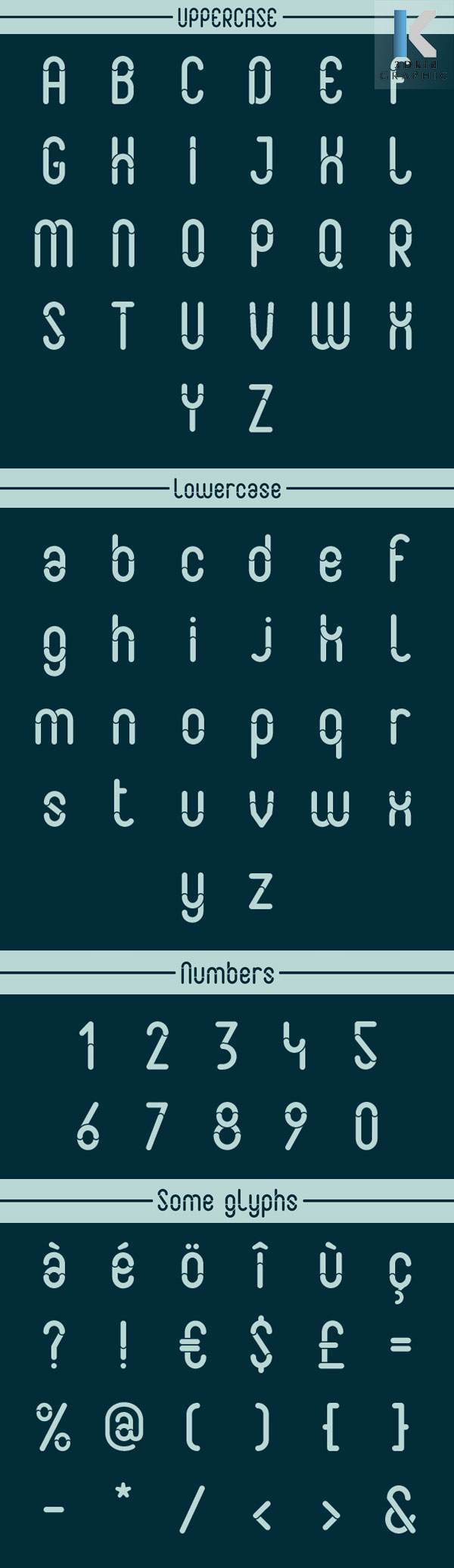
2. Font Kagome
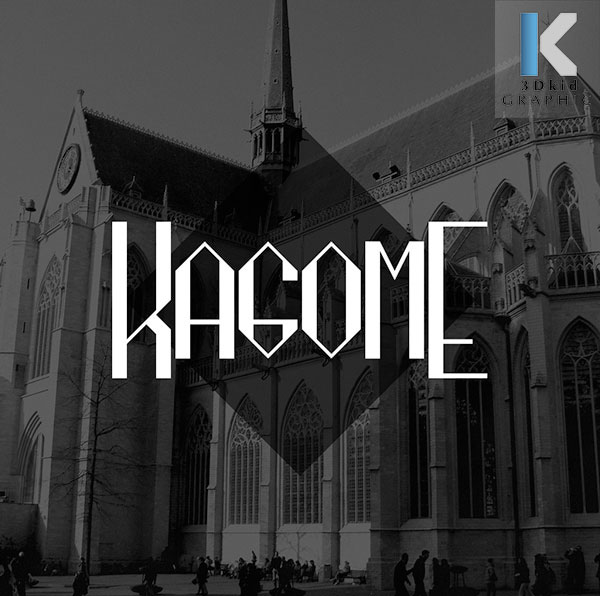
3. Font Daggerspuare
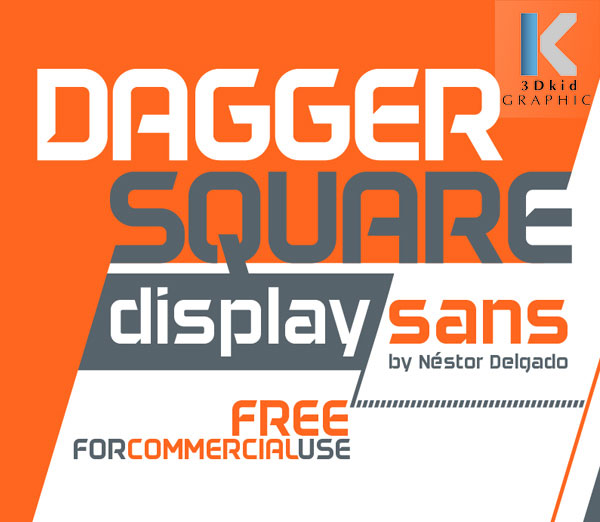
4. Font Monthoers
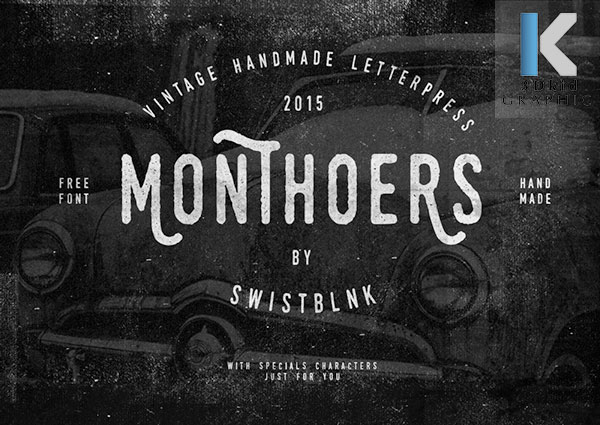
5. Font Nordic
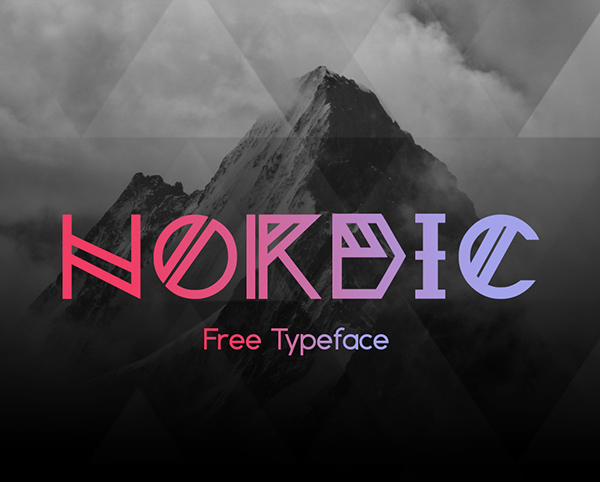
6. Font Moon
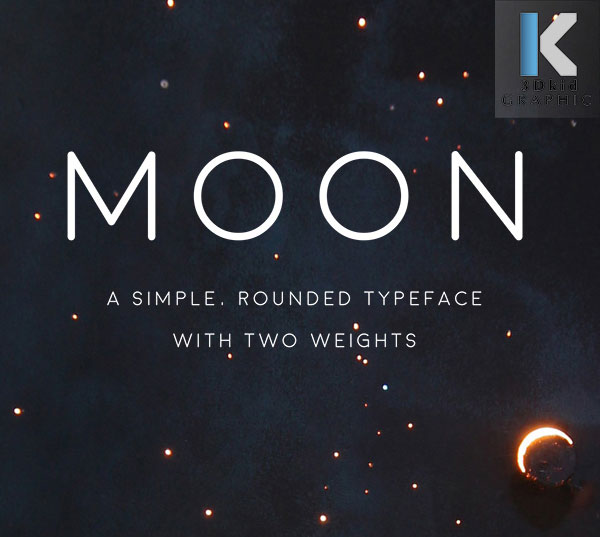
7. Font Perforgrama
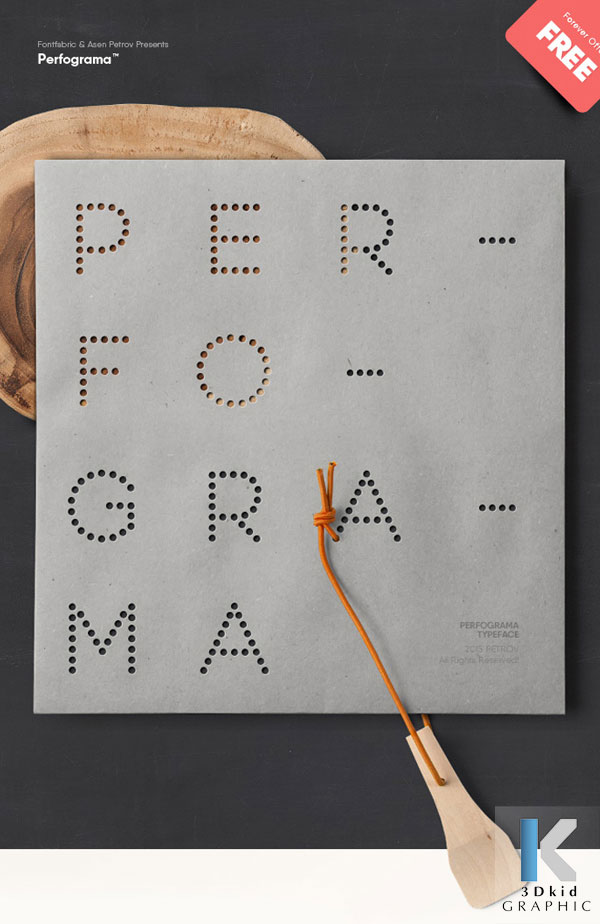
8. Font Maxwell
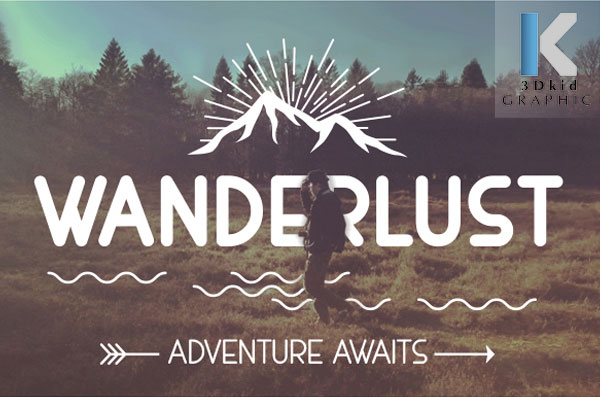
9. Font Valencia
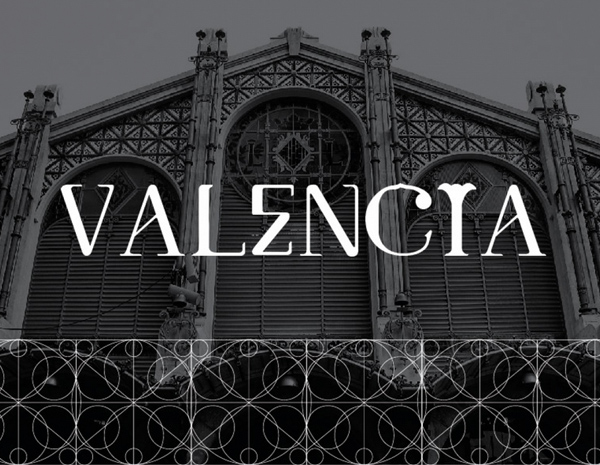
10. Font Sarendipitiy script